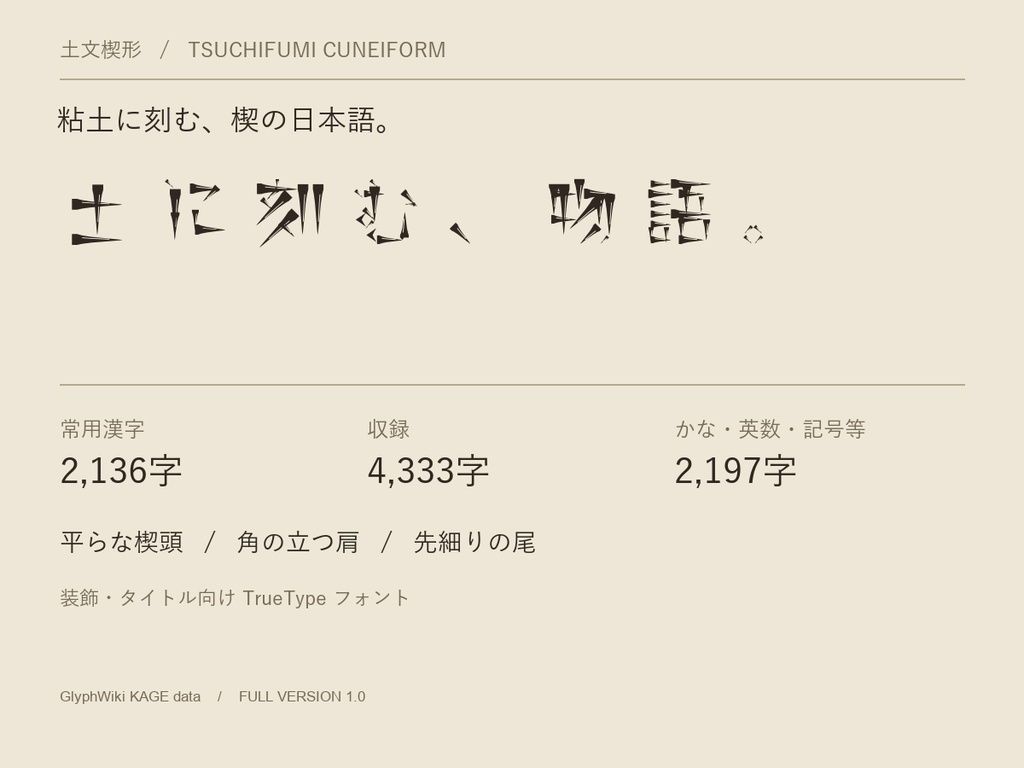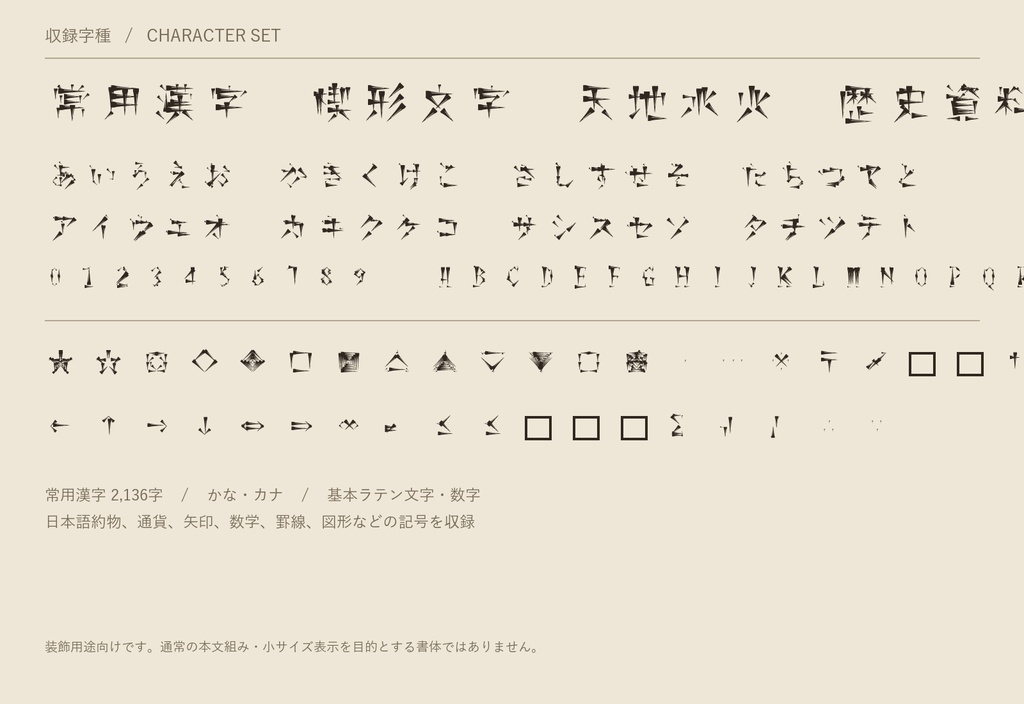
土文楔形|日本語楔形フォント Full 1.0
常用漢字2,136字を収録した、楔形刻印風の日本語装飾フォントです。GlyphWikiのKAGE字形配置をもとに、幅広側を平らに切った楔を組み直しました。 【収録】4,333字:常用漢字2,136字、ひらがな・カタカナ、基本ラテン文字・数字、約1,900種の記号(日本語約物、通貨、矢印、数学、罫線、囲み、図形など)。 【向いている用途】タイトル、ロゴ案、ゲーム・動画・同人誌の見出し、創作世界の演出。 【ご注意】本文向け・小サイズ向けの書体ではありません。実在の楔形文字を翻字するフォントではなく、日本語の字形を楔形風に再構成した装飾書体です。 【ライセンス】GlyphWikiの同梱ライセンスに基づき、商用利用・改変・再配布が可能です。詳細は同梱FONT_LICENSE.txtおよびGLYPHWIKI_LICENSE.txtをご確認ください。